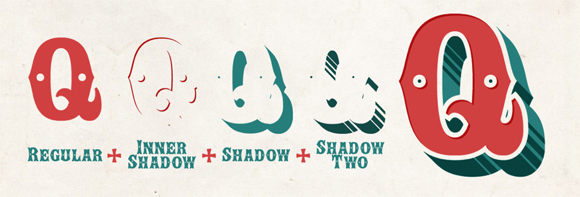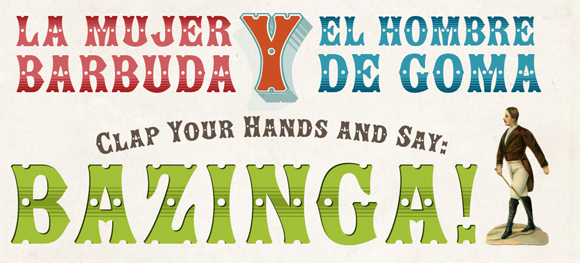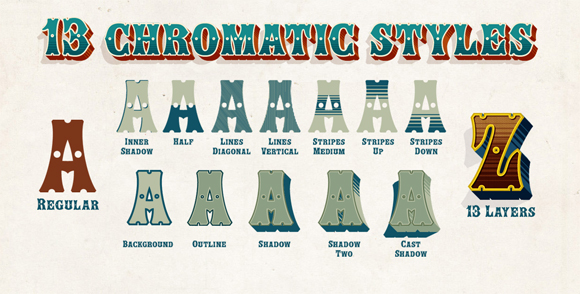
Nuestro tipoduro Juanjo López en alianza cósmica con la diseñadora Inés Atienza, nos presentan una tipografía espectacular. Bebiendo directamente de las mejores fuentes decimonónicas, Show es una tipografía digital que recrea los diseños de madera del siglo XIX, unas tipografías que alumbraron un nuevo periodo en el que los tipos «saltaron» de la página impresa del libro al póster pegado en la pared y que acompañaron a la naciente sociedad industrial.
Show, una tipografía de corte display, aporta unas características que multiplican su utilidad y versatilidad. Las fundiciones del XIX pusieron a disposición de los impresores unas tipografías a las que se podían añadir sombras y biseles intercambiando diferentes piezas y pasando la misma hoja varias veces por la prensa. Era la respuesta a la facilidad de aportar nuevos y atrayentes diseños de letras que aportaba la litografía y, de hecho, estas fuentes (conocidas en Inglaterra como chromatic type) llegaron a ser muy conocidas y utilizadas en la época.
En esta ocasión y aprovechando las facilidades del medio digital, estás características añadidas permiten multitud de posibilidades y ello, añadido a la gran colección de glifos que presenta la fuente, con soporte para diferentes idiomas centroeuropeos, hacen de Show una tipografía plenamente actual con un guiño al pasado que no dejará indiferente a nadie que se cruce con ella.